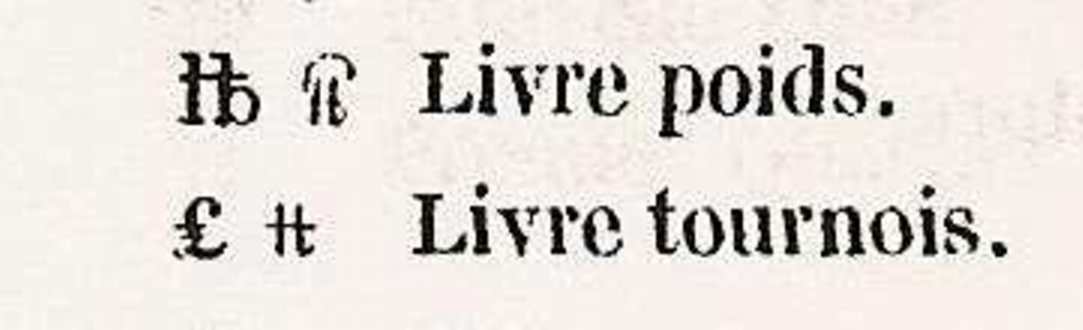
> Les sommes étaient toujours abrégées avec un caractère ressemblant au > dièse (#), mais sans la barre du bas, sans que cela signifie livres > tournois (ou parisis). Ah oui, ça (selon Théotiste) ? Mais je ne vois guère de ressemblance avec # et encore moins avec un dièse ! J.A.